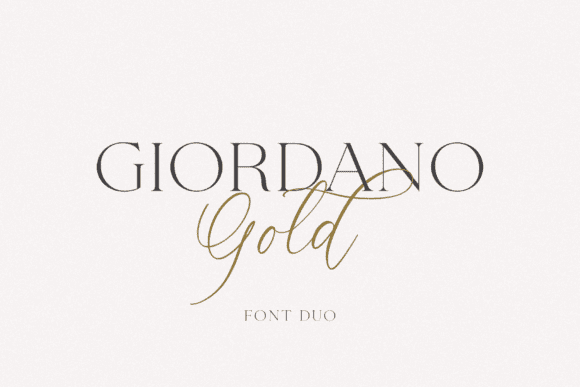
Giordano Gold - это красивый, тонко начертанный и элегантный дуэтный шрифт (шрифт и засечка).
Невероятно универсальный, этот шрифт подходит для широкого круга дизайнов, поднимая их на самый высокий уровень.